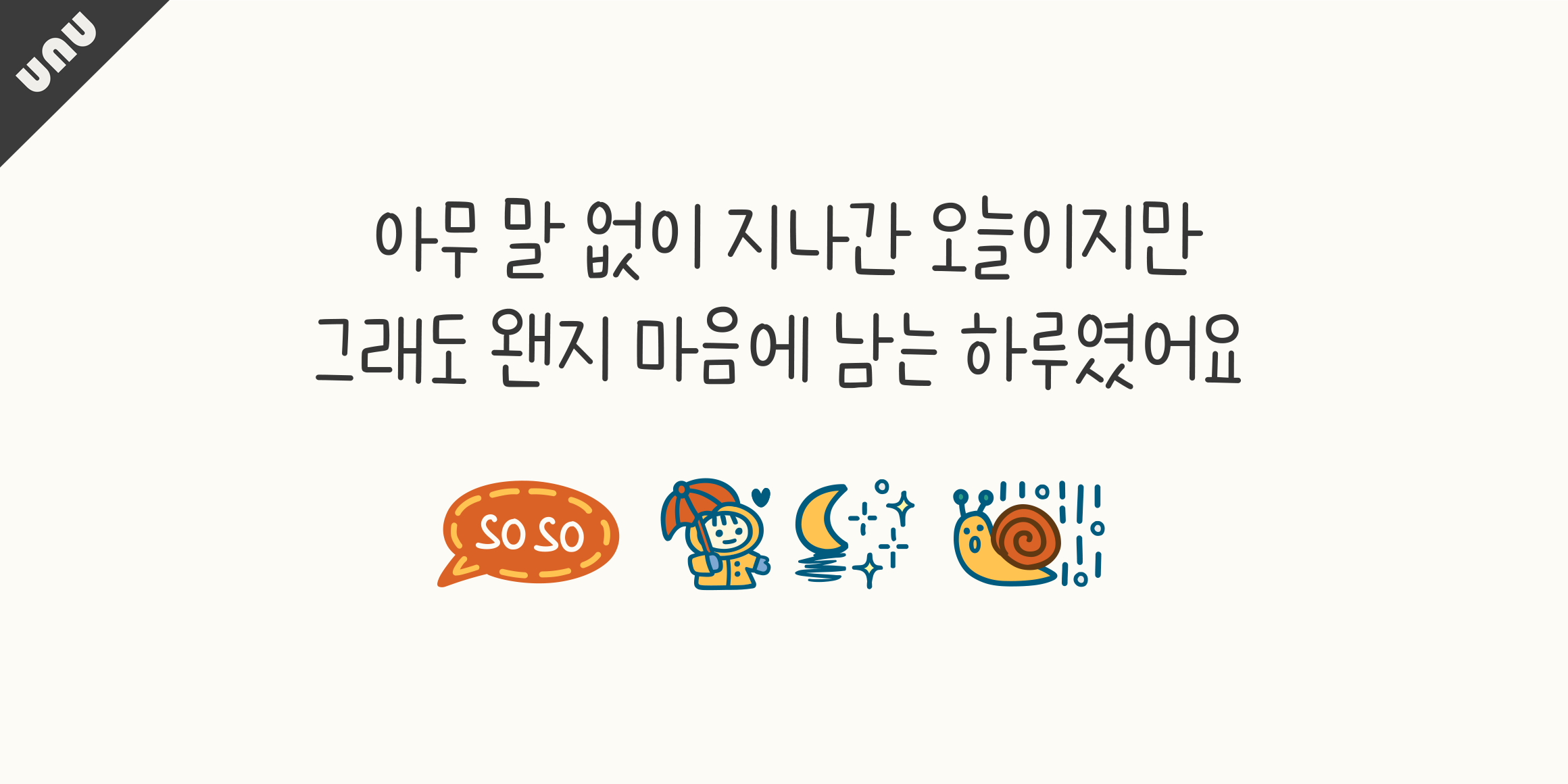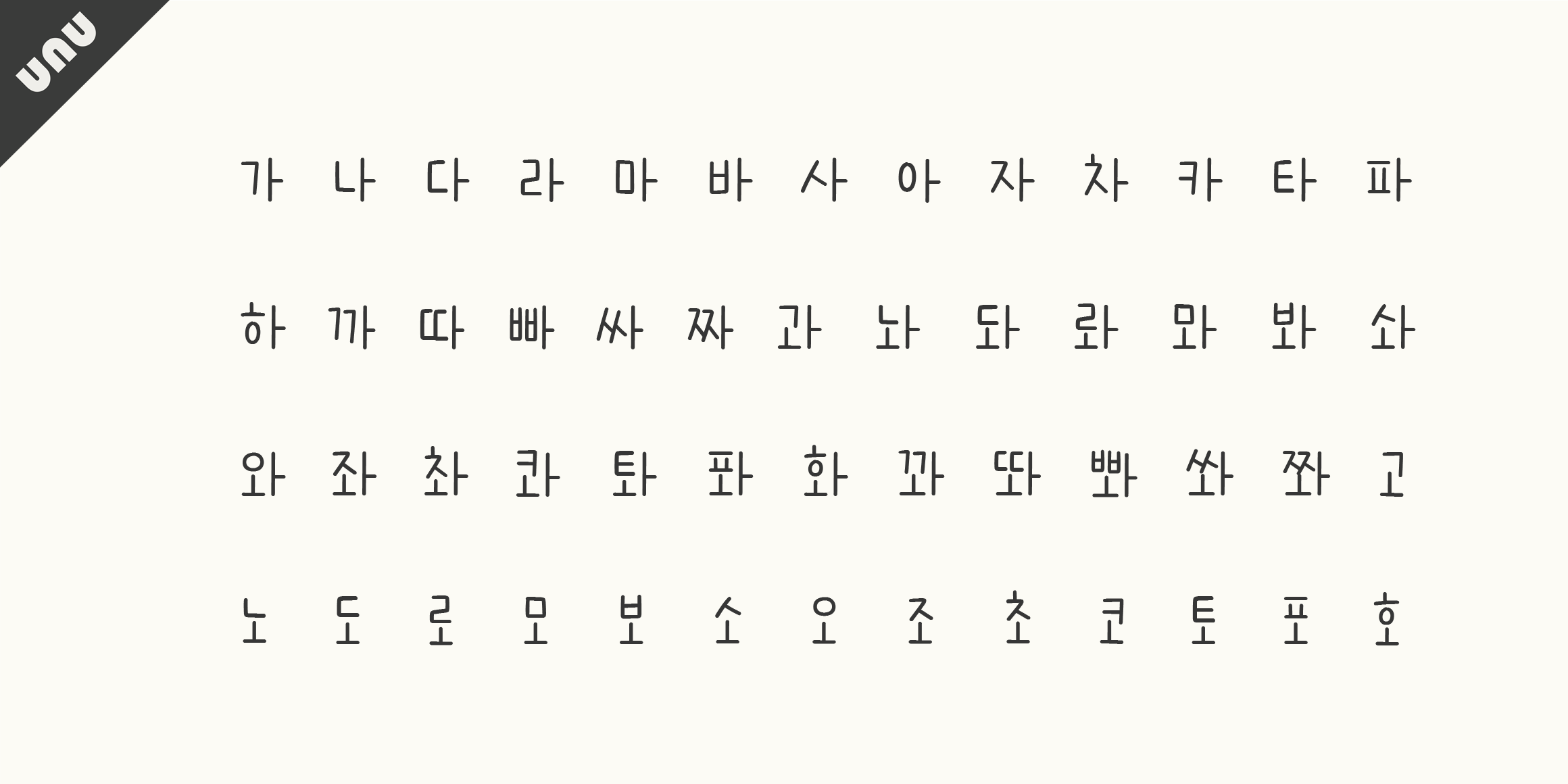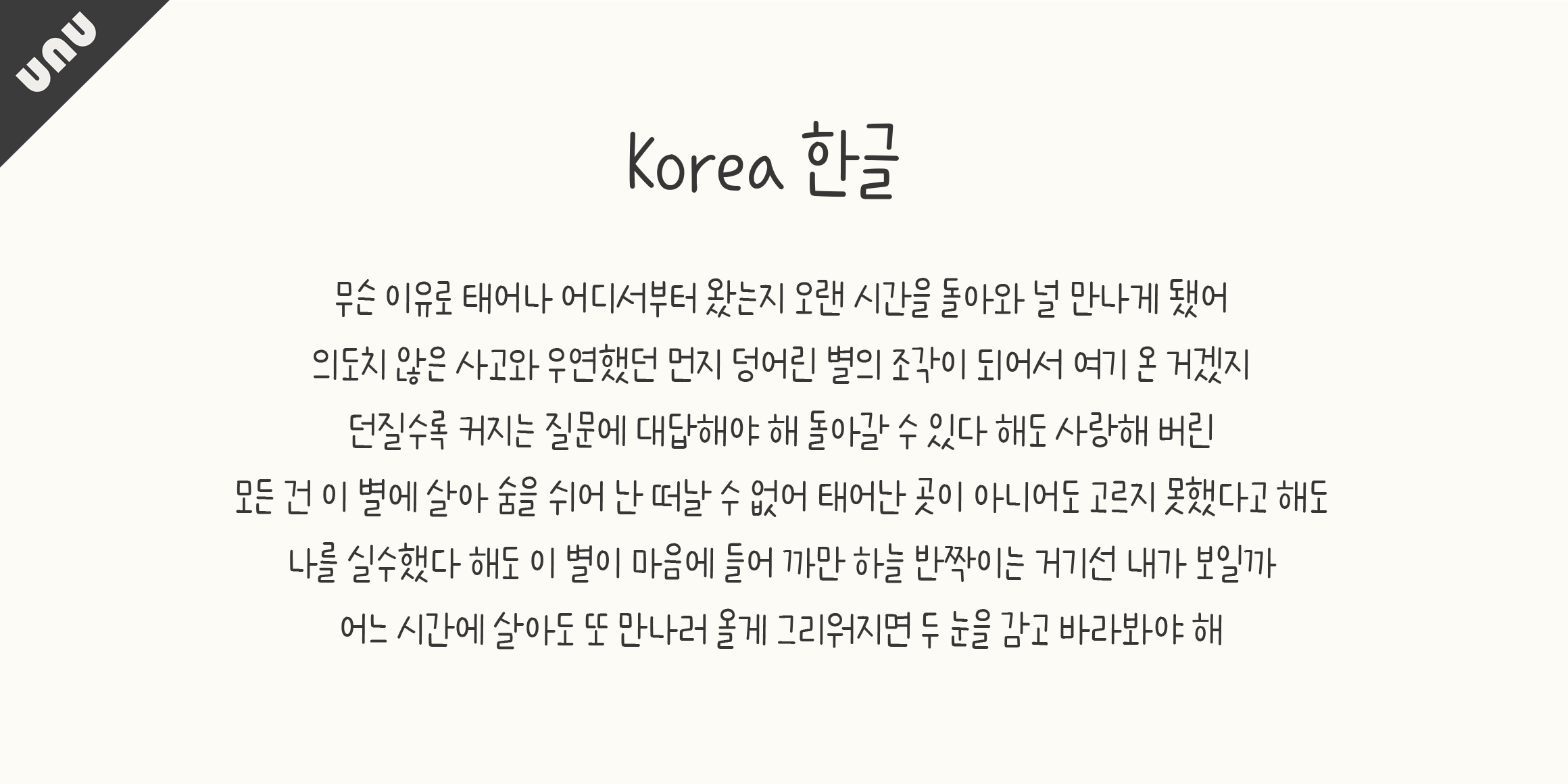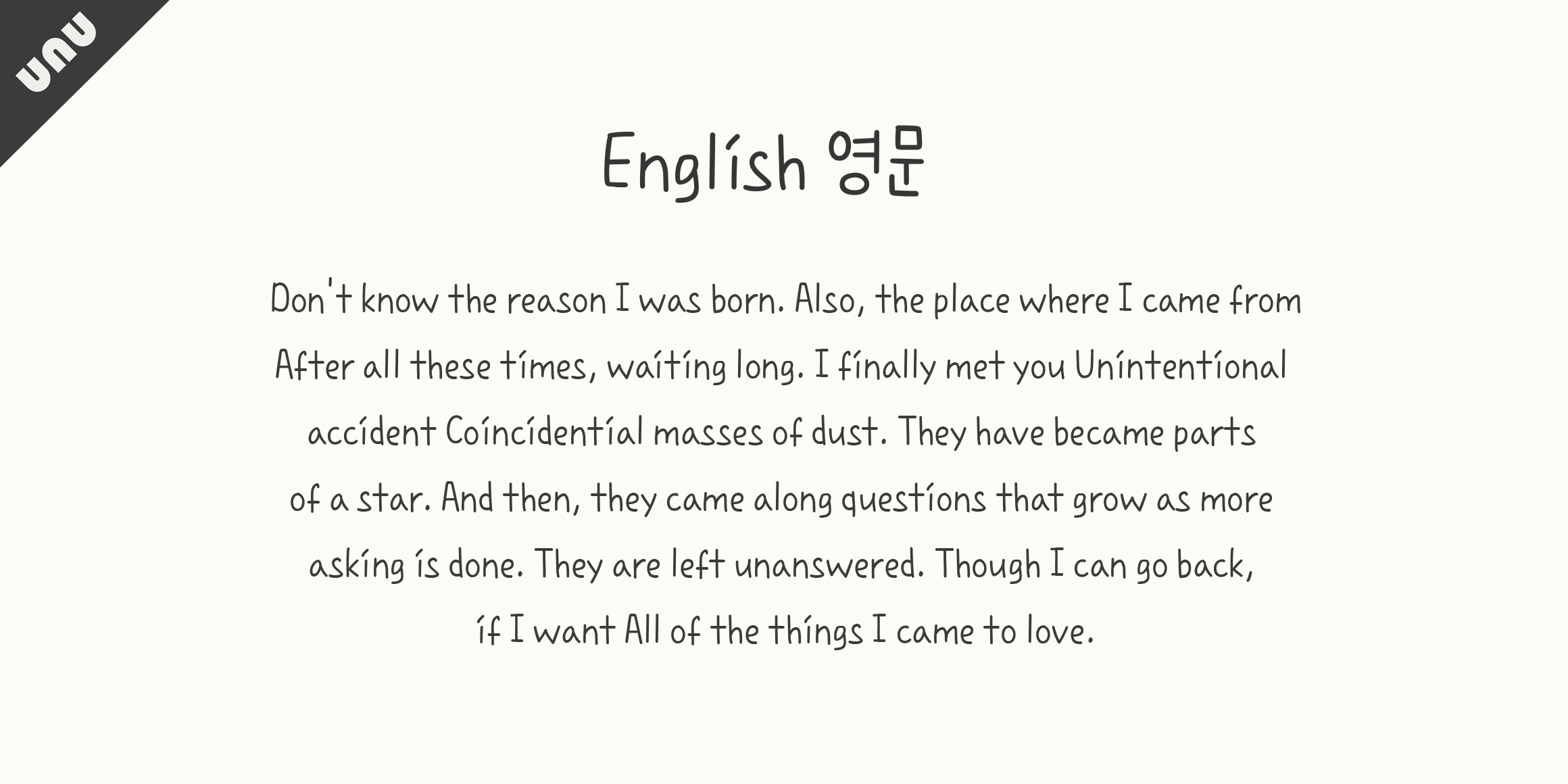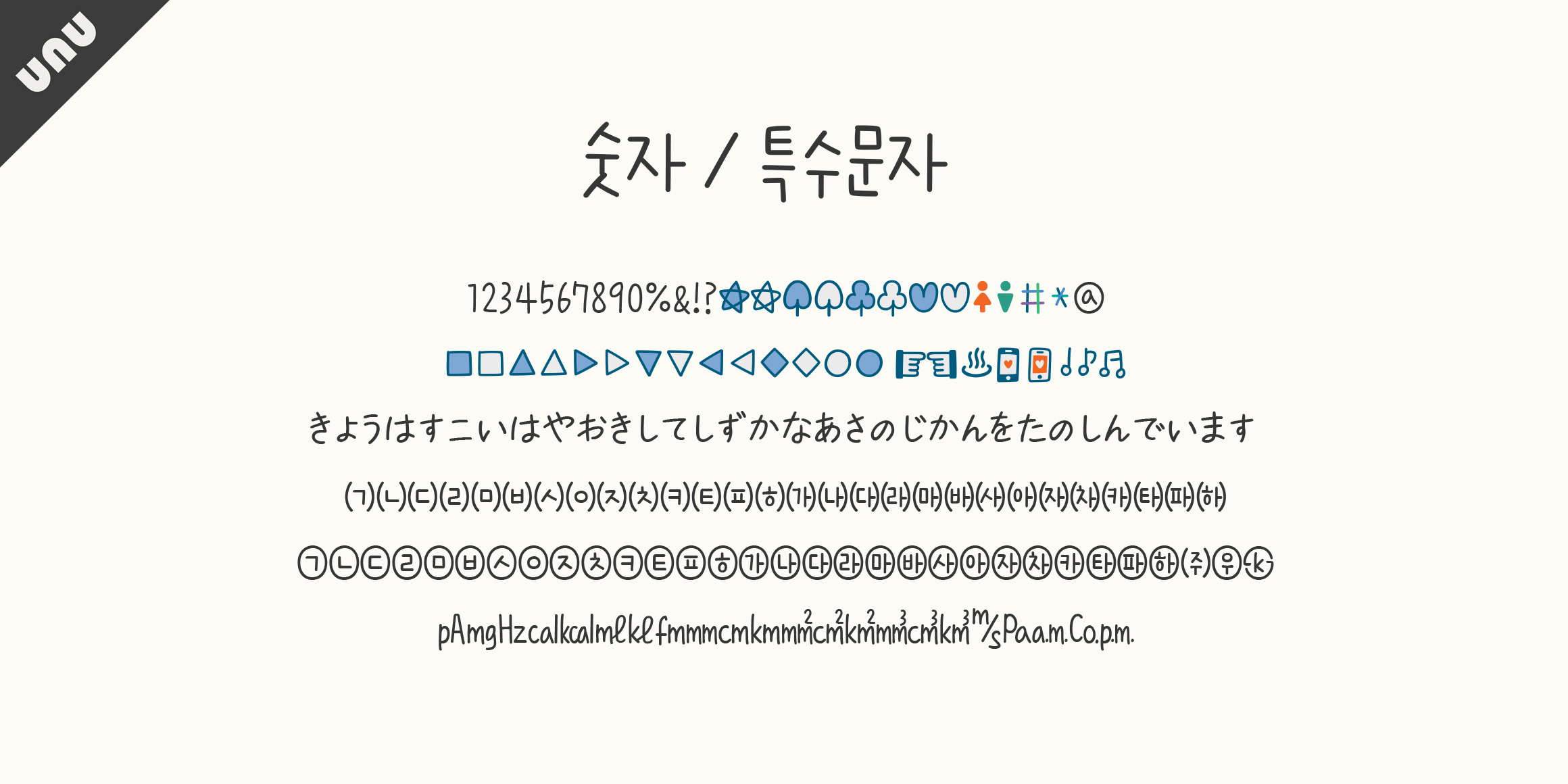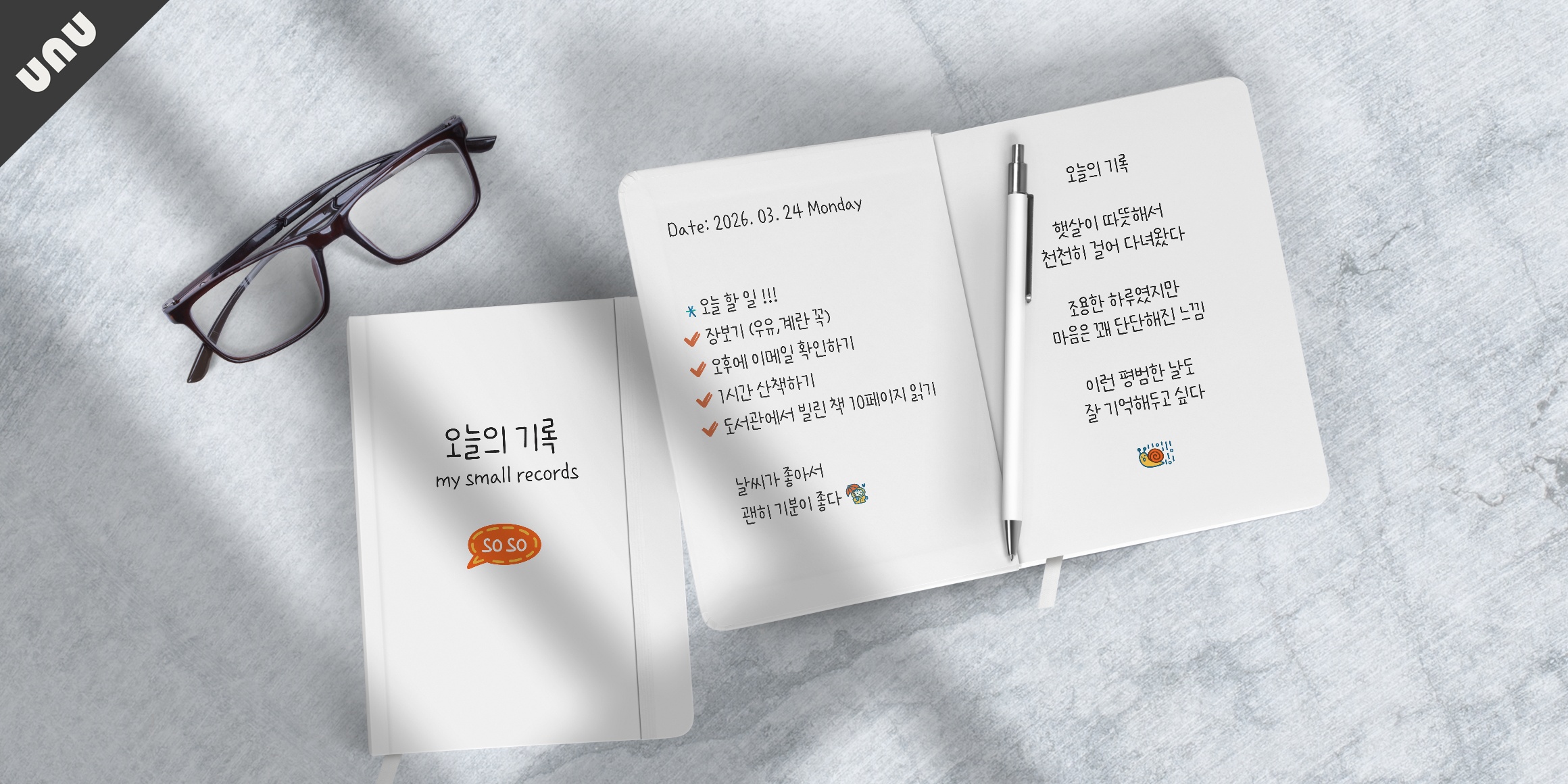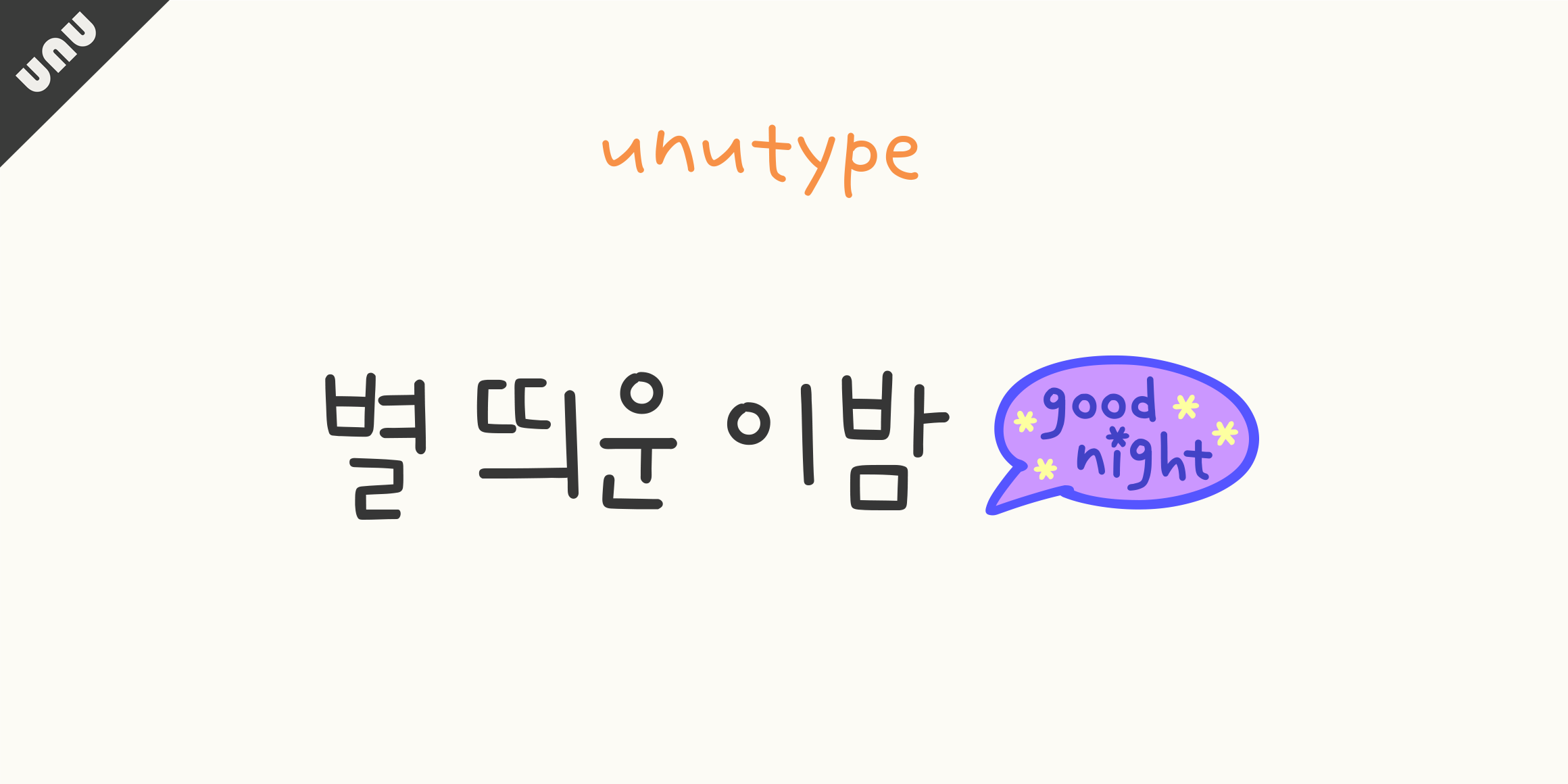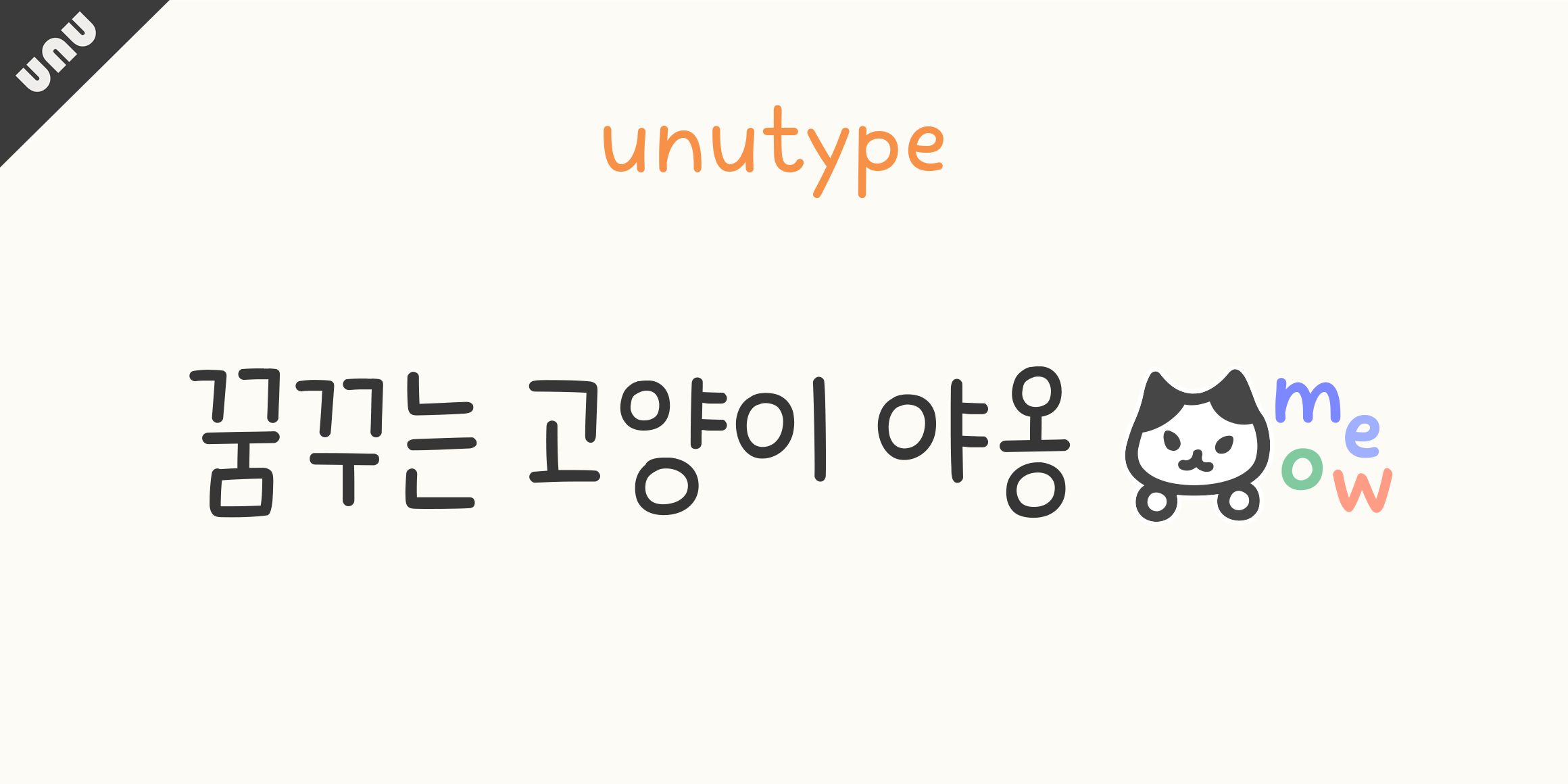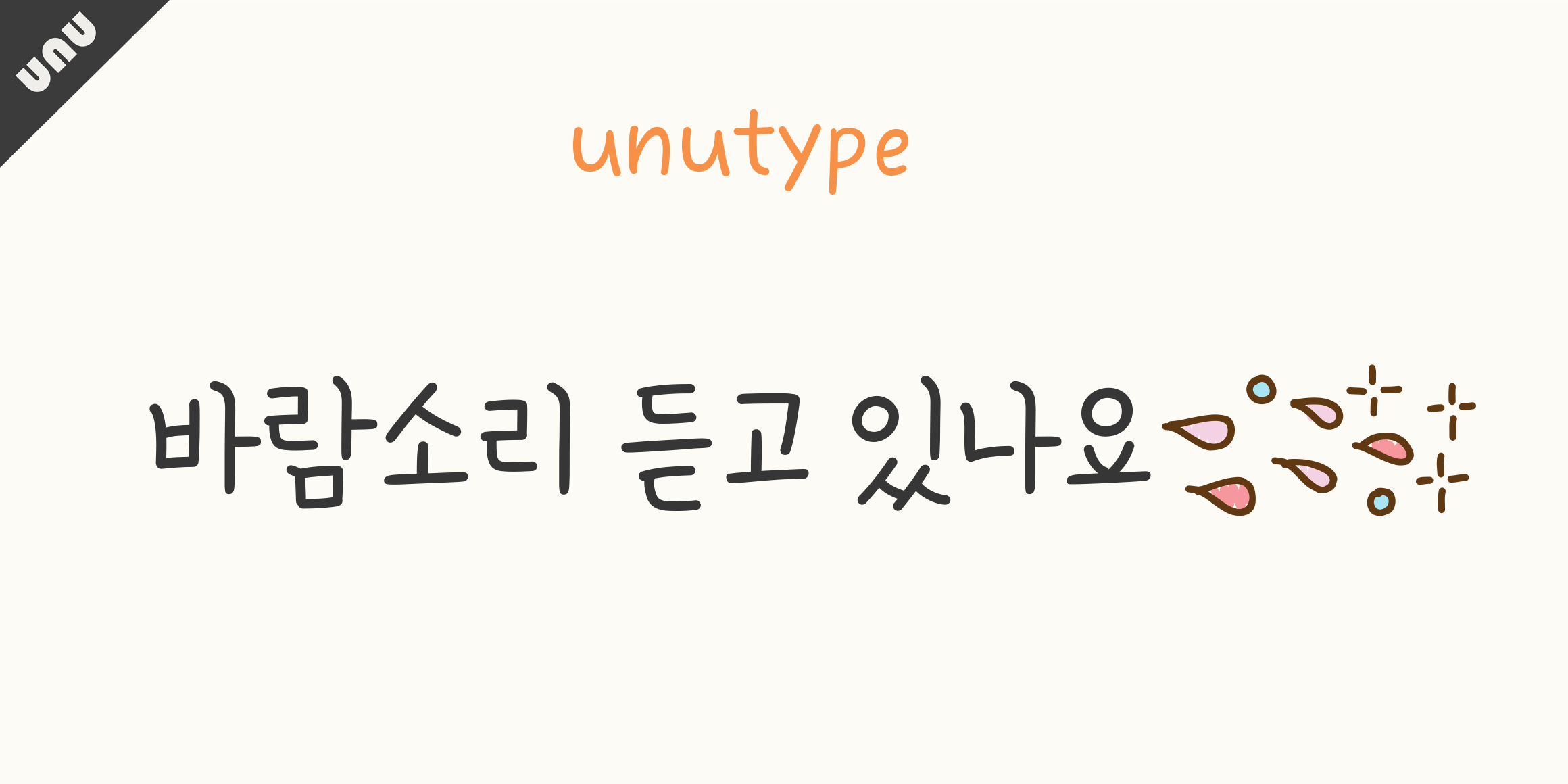
unu바람인것같이
이 서체는 자연스러운 글줄과 자소형태가 사랑스러운 손글씨입니다. 사랑하는 누군가에게 따뜻한 마음을 전하고 싶을때, 내 소중한 다이어리에 오늘을 기록하고 싶을때 추천드립니다. 유앤유서체는 당신의 따뜻한 마음을 전해드립니다.(컬러가 적용되지 않는 기기나 앱이 있을 수 있으며, 두껍게(Bold)처리시 두께 변화가 없을 수 있습니다.)
• 한글 11,172자 / 라틴 95자
• Script,손글씨
• unu바람인것같이 / unuLikethewind